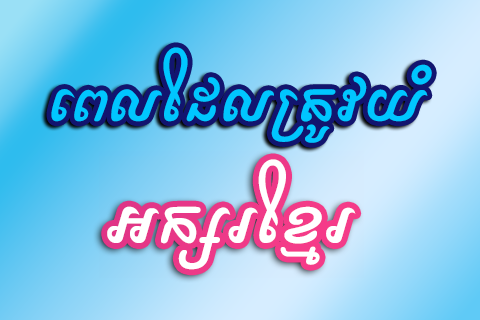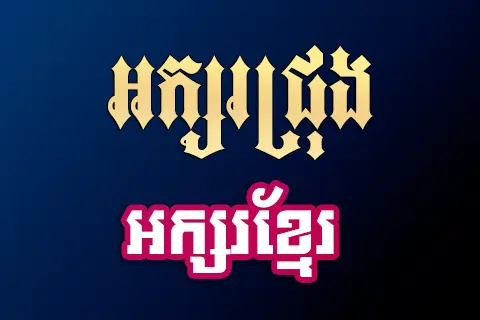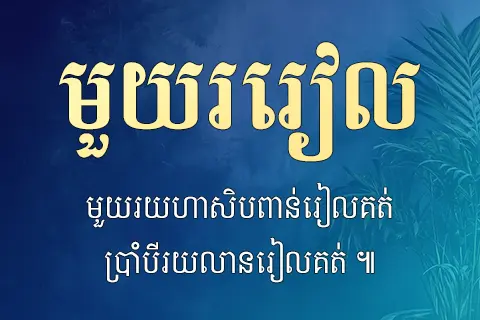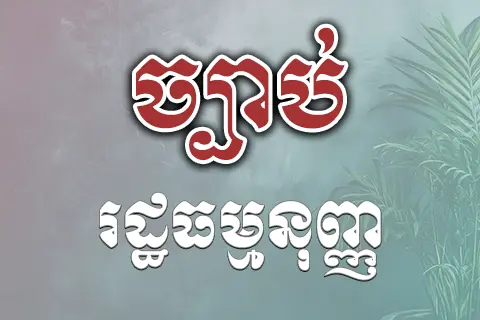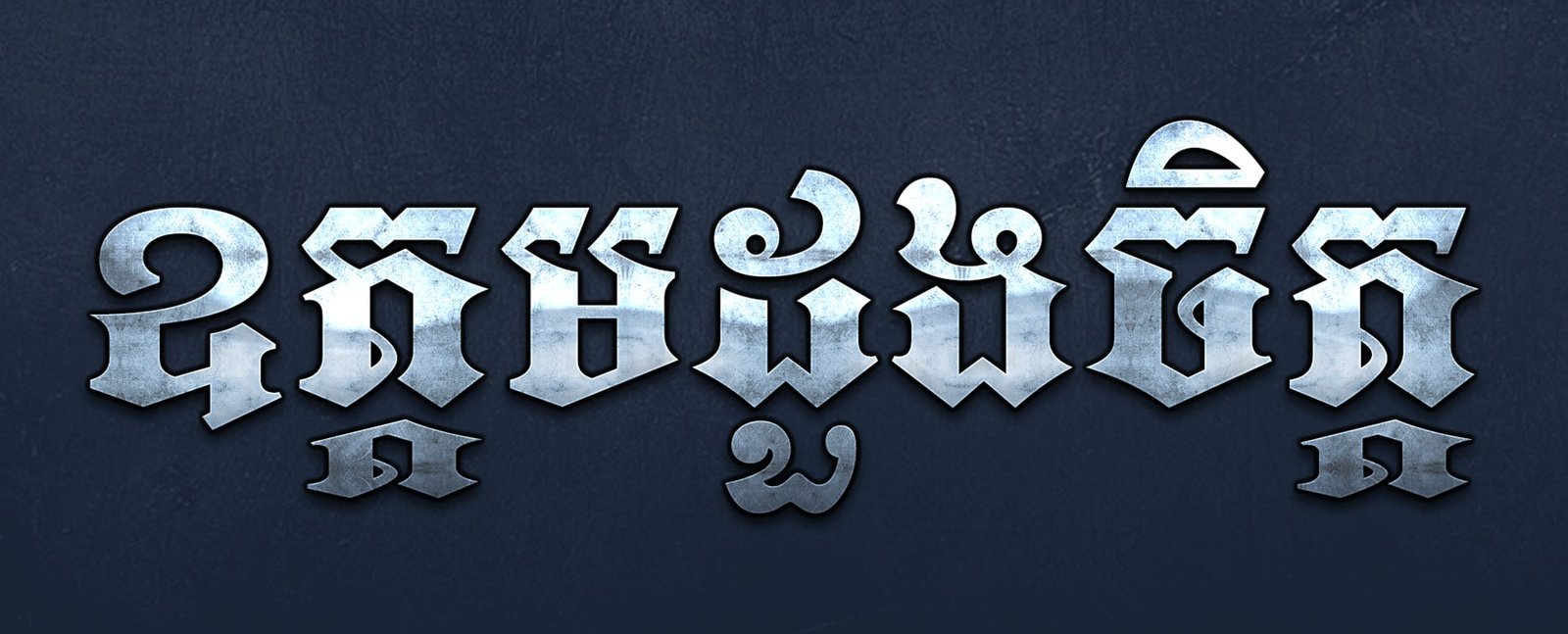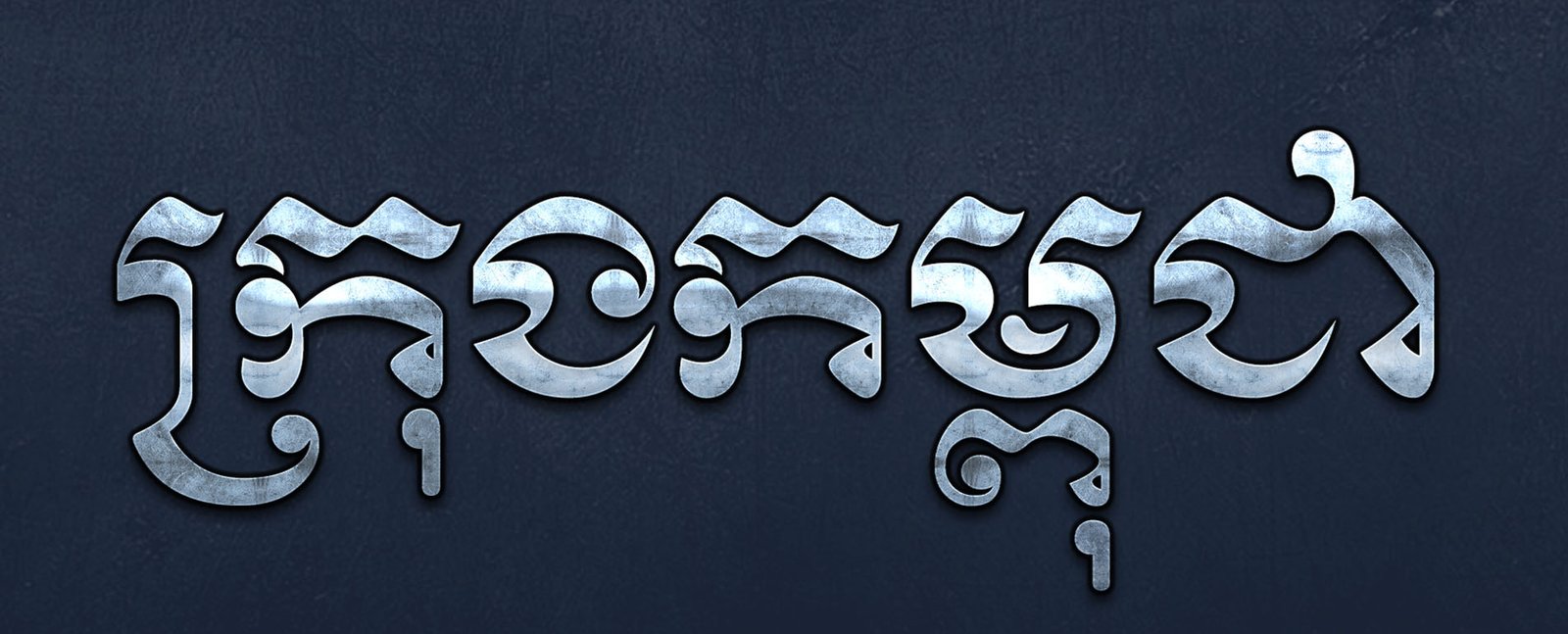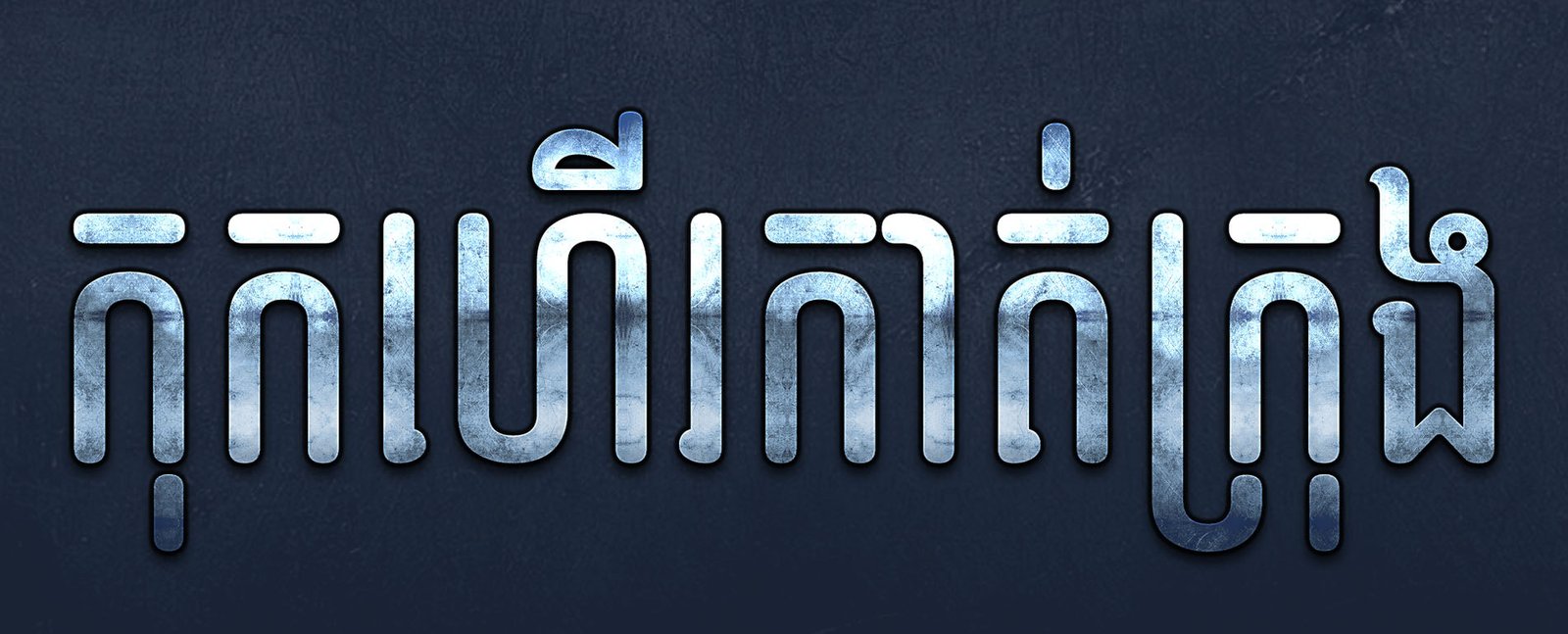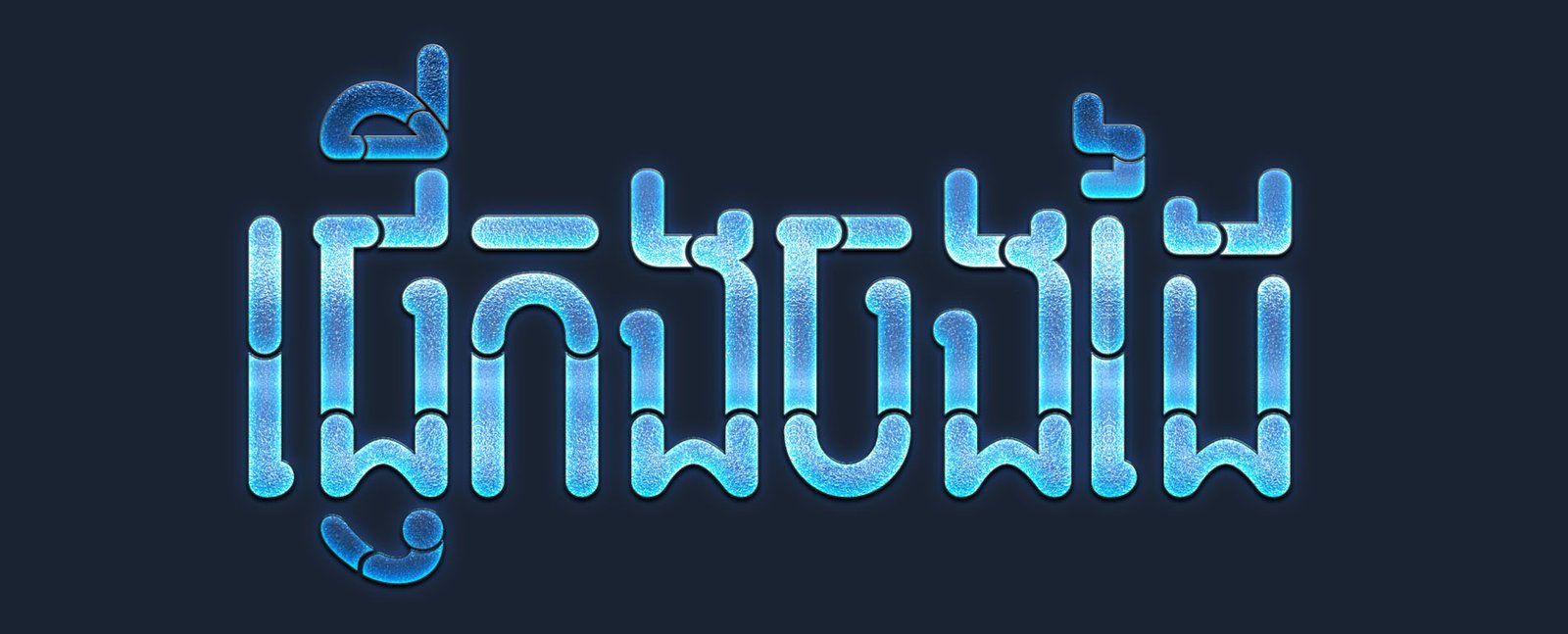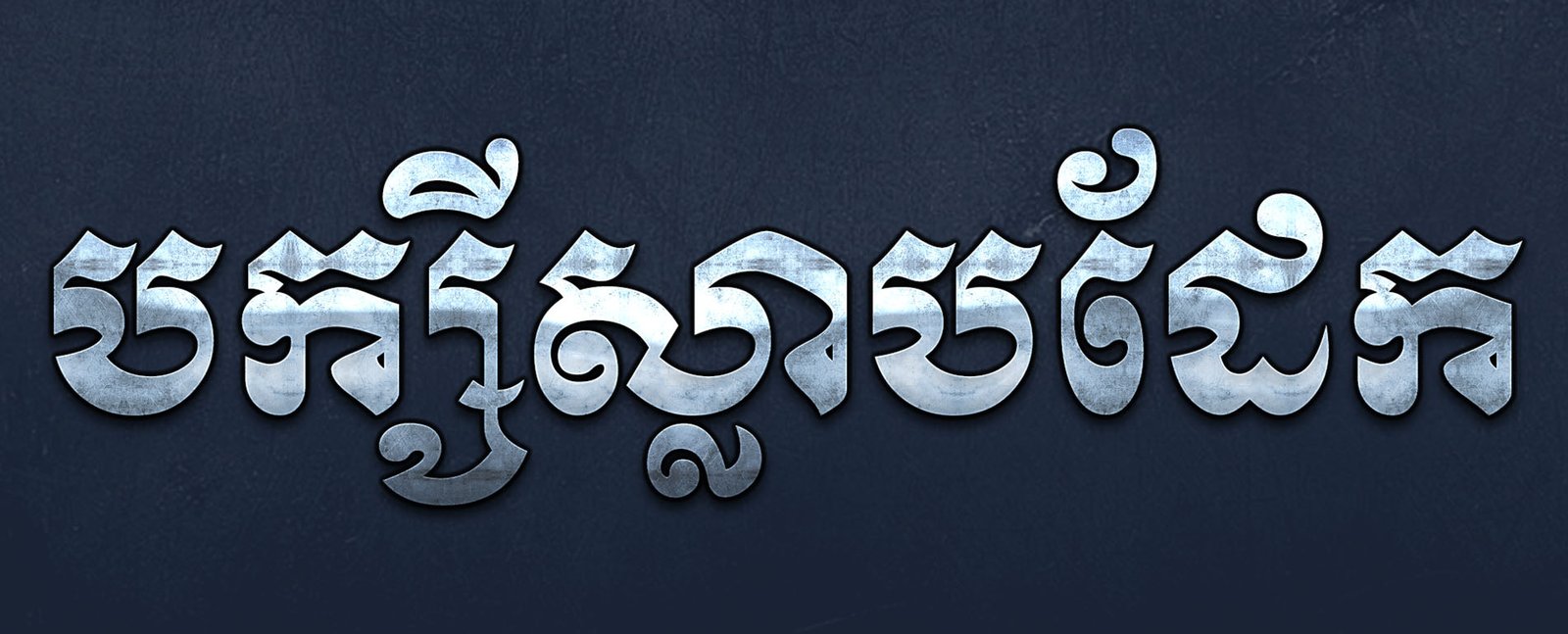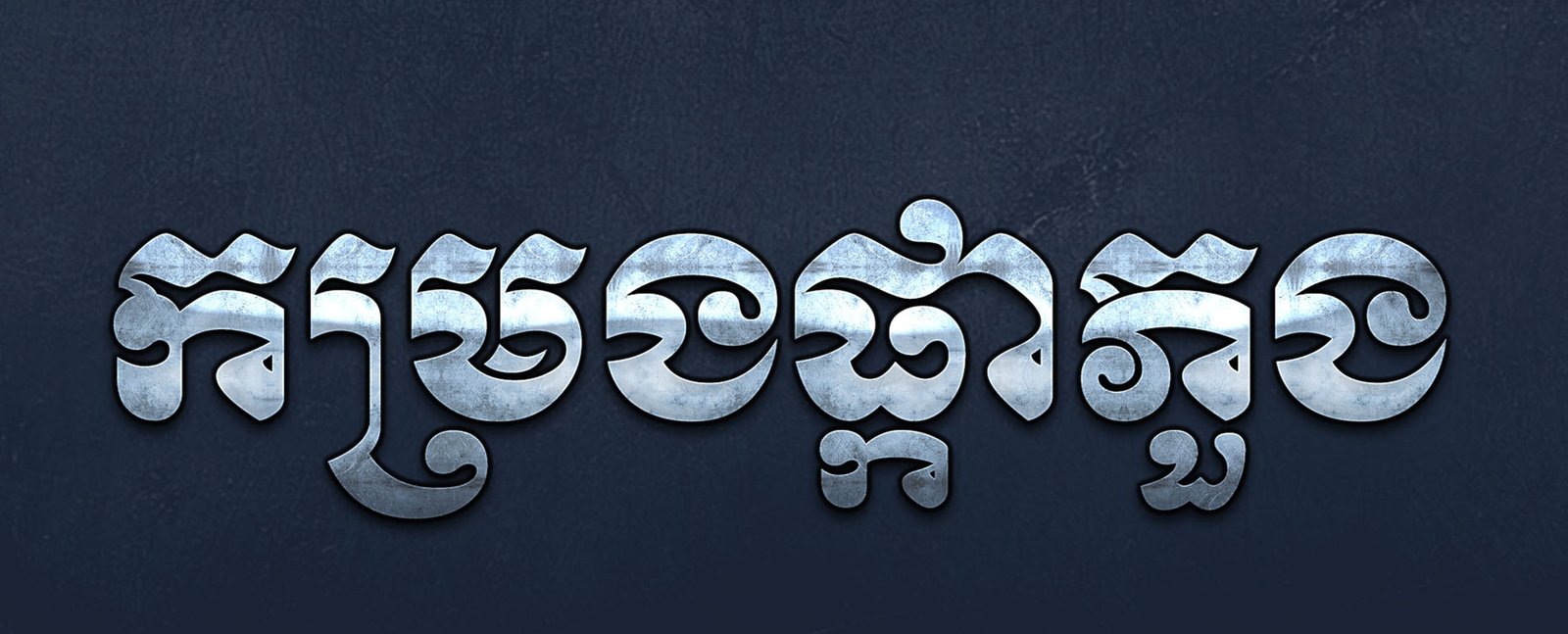
យល់ដឹងអំពីពុម្ពអក្សរ
អំពីអ្នករចនា
ពុម្ពអក្សរទាំងអស់នេះ គឺត្រូវបានរចនាឡើងដោយលោក ហៀប ឃឹម អ្នកសិក្សាមិនដែលស្គាល់មហាវិទ្យាល័យ ឬសាកលវិទ្យាល័យអ្វីទាំងអស់ ។ គាត់បានសិក្សានិងឆ្លៀតពេលទំនេរពីការងារដើម្បីបង្កើតឱ្យមានផលិតផលមួយចំនួនសម្រាប់បម្រើនូវសេចក្ដីត្រូវការរបស់អ្នកតាមដែលអាចធ្វើទៅបាន ។ អ្នកនឹងបានឃើញឬទទួលបាននូវផលិតផលថ្មីៗបន្តទៀតនៅក្នុងគេហទំព័រ Khimsoft ហើយនឹងដាក់ឱ្យប្រើប្រាស់ជាផ្លូវការតាមការសម្រេចចិត្តរបស់ខ្លួន ។
អំពីអក្សរយូនីកូដ
Unicode គឺជាស្តង់ដារមួយដែលវាត្រូវបានគេប្រើសម្រាប់អក្សរដែលមានភាពស្មុគស្មាញ ដែលខុសពីអក្សរប្រភេទ Latin ច្រើនទាក់ទងនឹងការបង្កើត ឬរៀបចំឱ្យវាអាចដំណើរការបានស្រួល មិនថាអក្សរប្រទេសណានោះទេឱ្យ តែប្រើប្រើស្តង់ដារ Unicode វាមានភាពលំបាកសម្រាប់អ្នករចនាទាំងការរចនានិងការត្រួតពិនិត្យរាប់រយដងក្នុងមួយពុម្ពៗ តែទោះជាលំបាកយ៉ាងណាយើងគ្មានជម្រើសអ្វីក្រៅពីដើរតាមផ្លូវដែលយើងមានសម្រាប់ជាប្រយោជន៍ ដល់សង្គមរបស់យើងនោះទេ ។
អំពីអក្សរ Khimsoft Latin
Khimsoft Latin គឺជាស្តង់ដារពុម្ពអក្សរខ្មែរប្រភេទឡាតាំងដែលត្រូវបានរចនាឡើងដើម្បីជួយសម្រួលដល់អ្នកប្រើប្រាស់អក្សរខ្មែរសម័យ Limon ឱ្យបានប្រសើរជាងមុន ប្រសើរនៅត្រង់ថាមានទំហំអក្សរស្មើនឹងអក្សរប្រភេទ Unicode, ការវាយក៏ស្រដៀងគ្នានឹងអក្សរយូនីកូដ, អាចដំណើរការបានគ្រប់កម្មវិធី មិនទាមទារ Normal dot, Normal dotm អ្វីនោះទេ ជាពិសេសម្រាប់អ្នកប្រើជាមួយនឹង macOS ឬនៅលើ Windows ដែលមានគេនិយមប្រើជាមួយនឹងកម្មវិធីកាត់វីដេអូឬមួយក៏កម្មវិធីស្ថាបត្យកម្មដូចជា AutoCAD ជាដើម ។
អំពីប្រភេទពុម្ពអក្សរ
ចំពោះប្រភេទពុម្ពអក្សរ យើងខ្ញុំបានរចនាឡើងសម្រាប់ប្រើប្រាស់តាមការណ៍ដែលអាចប្រើទៅបានរួមមាន៖ ពុម្ពអក្សរក្រសួងមានចំនួន 34 ស្ថាប័ន ដែលគិតជាអក្សសរុបមាន 326 ឯកសារ ហើយ នឹងអក្សរសម្រាប់អត្ថបទ, អក្សរផ្នែក Design អក្សរផ្នែកអប់រំ ។ល។
អក្សរប្រភេទមាតិកា (Content)
ចំពោះពុម្ពអក្សរដែលជាប្រភេទមាតិកា ជាទូទៅត្រូវបានដាក់ឈ្មោះថា Content នៅខាងចុងឈ្មោះពុម្ពអក្សរនីមួយៗ ឧទាហរណ៍ថាអក្សរ ឈ្មោះ Khimsoft Royal ដូច្នេះអក្សរមាតិកាត្រូវបានកំណត់យកឈ្មោះថា Khimsoft Royal Content ។ បញ្ជាក់ថាអក្សរមាតិកា គឺជាអក្សរដែលរក្សាលំនាំអក្សរដើមនីមួយៗទាំងស្រុងគ្រាន់តែអក្សរប្រភេទនេះត្រូវបានបន្ថែមឱ្យវាធ្វើការបកប្រែ ពីលេខឡាតាំងពី 0-9 មកលេខខ្មែរពី ០-៩ តែប៉ុណ្ណោះ ។ ជាទូទៅគឺធ្វើឡើងជាមួយអក្សរប្រភេទ Unicode ចំពោះអក្សរប្រភេទ Khmer-Latin គឺមិនចាំបាច់នោះទេ ។
អក្សរសំខាន់ៗ
ខាងក្រោមនេះគឺជាក្រុមអក្សរដែលត្រូវបានកំណត់បង្ហាញជូនលោកអ្នក ដើម្បីទទួលបាននូវទិដ្ឋភាពស្ដីពីរចនាប័ទ្មអក្សរខ្មែរប្រភេទយូនីកូដ (មិនមានអក្សរខ្មែរឡាតាំងទេ) ។
(Group Fonts)
អក្សរមូល (Heading Font)
អក្សរអត្ថបទ (Body Font)
អក្សររចនាប័ទ្ម (Style)
បទពិសោធន៍ក្នុងការរចនា - Design Experience
ការស្រមើស្រមៃ, ការច្នៃប្រឌិត, និងការសាកល្បង, កំហុស, និង ការកែតម្រូវ
ភាពស្ងប់ស្ងាត់ និងសុខភាពល្អ គឺជាកត្តាចម្បងក្នុងការសម្រេចបាននូវឆន្ទៈ
អ្វីៗអាចនឹងកើតឡើងបាន អាស្រ័យលើក្ដីស្រមើស្រមៃរបស់យើង ហើយក្ដីស្រមៃទាំងនោះវា អាស្រ័យលើយើងជាអ្នកគ្រប់គ្រងវាបានទៅតាមលទ្ធភាព និងសមត្ថភាពប៉ុណ្ណោះ វាមិនមានអ្វី ដែលកើតឡើងដោយមិនមានហេតុផល ឬការគិតគូរនោះទេ លើកលែងតែរឿងដែលមិនមាន ជាប្រយោជន៍ (រឿងអាក្រក់ៗ) តែប៉ុណ្ណោះ ដែលវាកើតឡើងដោយយើមិនប្រាថ្នា ។
តួព្យញ្ជនៈ និងស្រៈ
អក្សរខ្មែរជាទូទៅយើងដឹងហើយថាមានព្យញ្ជនៈ (កខគឃង ចឆជឈញ ដឋឌឍណ តថទធន បផពភម យរលវសហឡអ) និងស្រៈ( ា ិ ី ី ឹ ឺ ុ ូ ួ ើ ឿ ៀ េ ែ ៃ ោ ៅ ុំ ំ ាំ ះ េះ ុះ ោះ) តែយើងនៅមានអក្សរពីរទៀតដែលមិនប្រើប្រាស់គឺ “ឝ” និង “ឞ” ។ ដ្បិតថាអក្សរពីរនេះមិនសូវលើកយកមកប្រើក៏ដោយក៏ពុម្ពអក្សរ របស់យើងមានពេញលេញសម្រាប់ប្រើប្រាស់ក្នុងការសរសេរដែរដូចជា៖ ប្រទេឝក្មេរជាដើម។
តួអក្សរ "ឝ"
អក្សរ ឝ, អានថា “ស.គ” យើងនៅតែប្រើក្នុងការកត់ត្រាប្រវត្តិដដែល គ្រាន់តែអក្សរនេះ ក្មេងៗខ្លះមិនទាន់ដឹងទេសូមចុចលើតំណខាងក្រោមនេះដើម្បីស្វែងយល់បន្ថែមទៀត ។
តួអក្សរ "ឞ"
ចំពោះអក្សរ ឞ, អានថា “ស.ប” គឺជាអក្សរ ទីបពីរបន្ទាប់ពីអក្សរ ឝ ដែលយើងមិនប្រើជាផ្លូវ ការបច្ចុប្បន្ន តែយើងនៅប្រើតែជើងទេ គឺជើងស  (្ស) នេះហើយ ។
អំពីលេខ
លេខខ្មែរត្រូវបានរចនាឡើងខុសៗគ្នាទៅតាម ប្រភេទនៃពុម្ពអក្សរនីមួយៗ ។ សម្រាប់អក្សរ ប្រភេទទូទៅគឺមានពី ០-៩ និងពី 0-9 ដែលជាលេខឡាតាំង នេះសម្រាប់អក្សរទូទៅ តែ បើជាអក្សរមាតិកា វានឹងដូរលេខពី 0-9 ទៅ ជា ០-៩ ជាលេខខ្មែរ ។
អំពី Khmer Symbol
Khmer Symbol គឺសំដៅលើលេខភាសា ខ្មែរដែលមានដូចជាលេខ បឋមាសាឍ, លេខទុតិយាសាឍ និងលេខអត្តៈ ។ តែអក្សរមួយចំនួនយើងមិនបានបង្កើតវានោះទេ ជាពិសេសអក្សរប្រភេទក្រាហ្វិក Design ។
អំពីពុម្ពអក្សរ
Khimsoft Latin
ពុម្ពអក្សរ Khimsoft Latin មានប្រមាណជាង ៨០ ប្រភេទ ហើយអក្សរនេះបើធៀបនឹងអក្សរ Limon គឺខុសគ្នាច្រើនដូចជា អក្សរ បា ប៉ា ញ ញា ញ៉ា ញ៉ៅ ឫ ឬ ឭ ឮ ឯ ឰ ឳ ឱ ឳ ឨ ឥ ឦ គឺត្រូវបានរចនាពេញលេញ ហើយមិនតែប៉ុណ្ណោះអក្សរនេះអាច ឱ្យអ្នកវាយបានដូចជា ទឡ្ហីករណ៍ លក្ស្មី បានធម្មតា ។ ចំណែកឯរបៀបប្រើប្រាស់ស្រៈពេញតួ ឬ វណ្ណយុត្តិ គឺដូចគ្នានឹងយូនីកូដស្ទើរទាំងស្រុង ។ សូមពិនិត្យមើលការបង្ហាញត្រួសៗដូចខាងក្រោម ៖